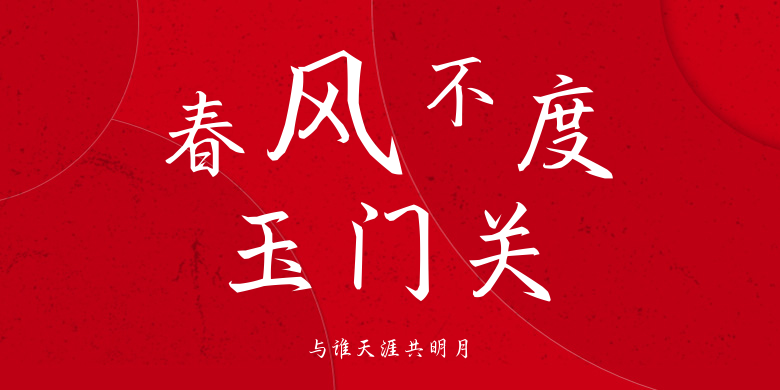
与谁天涯共明月
与谁天涯共明月,这款字体结构工整、笔画清晰,兼顾美观与易读性,适用于标题、正文、海报、包装、LOGO 等多种场景。字形优雅稳定,风格百搭耐看,适配日常排版与创意设计,让文字呈现更舒适、更具质感。与谁天涯共明月一笔一画,皆是细节,以均衡的比例、流畅的线条打造舒适视觉体验,字形端正大气,风格简约现代。无论是商业设计、品牌宣传还是日常排版,都能轻松驾驭,让文字更有格调与力量。与谁天涯共明月字体下载。